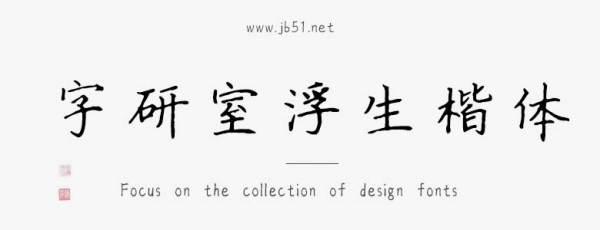
字研室浮生楷體是字研室出品的藝術(shù)字體,字體筆觸適中,字形端正,具有很好的視覺感,適合應(yīng)用于藝術(shù)設(shè)計(jì)、平面宣傳設(shè)計(jì)、網(wǎng)頁(yè)設(shè)計(jì),書法字帖等領(lǐng)域。有需要的朋友快來(lái)本站下載使用吧。